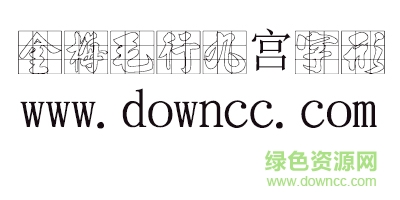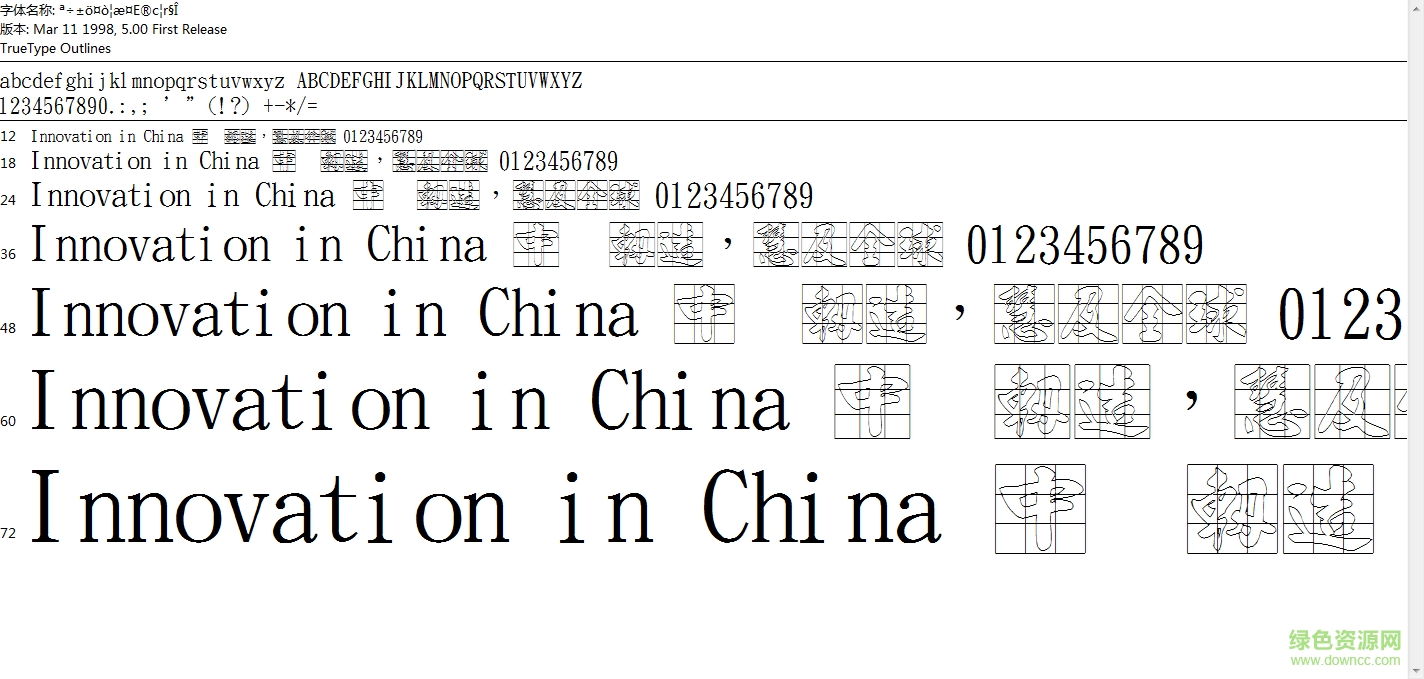
金梅毛行九宮字形字體是金梅字體庫(kù)中很有特點(diǎn)的一類(lèi)字體。這類(lèi)字體輸出的文字帶有九宮格,常用來(lái)進(jìn)行文字排版設(shè)計(jì)標(biāo)題使用!喜歡的用戶(hù)趕快來(lái)下載體驗(yàn)吧。
金梅毛行九宮字形是一款端正大氣的藝術(shù)字體,此款字體每個(gè)字都自帶田字格,字體為空心,比較顯眼,可應(yīng)用于廣告設(shè)計(jì)、平面設(shè)計(jì)、包裝印刷等,歡迎來(lái)綠色資源網(wǎng)下載使用!